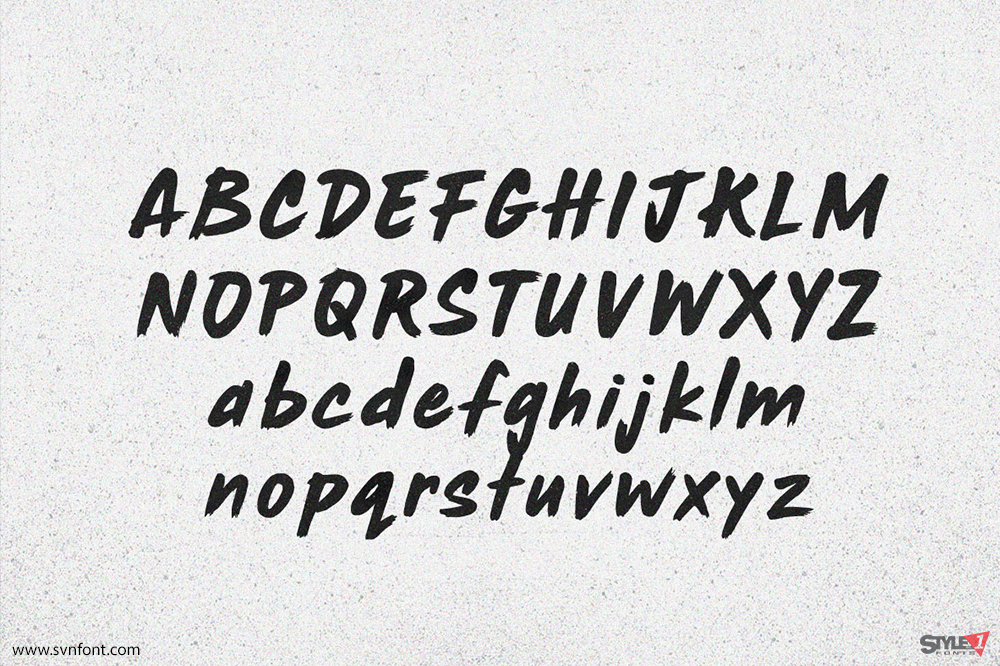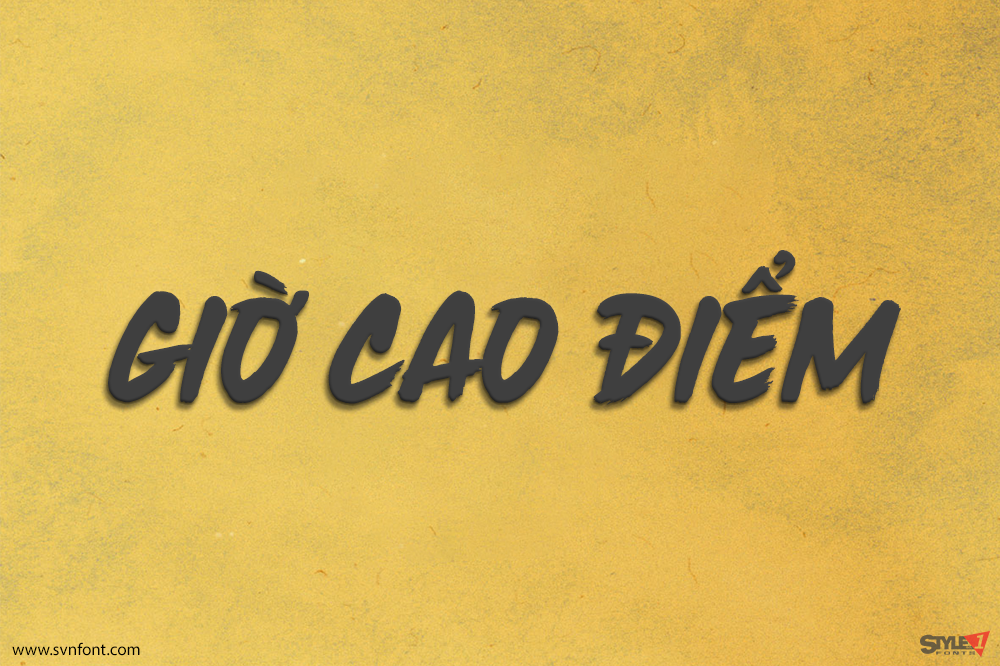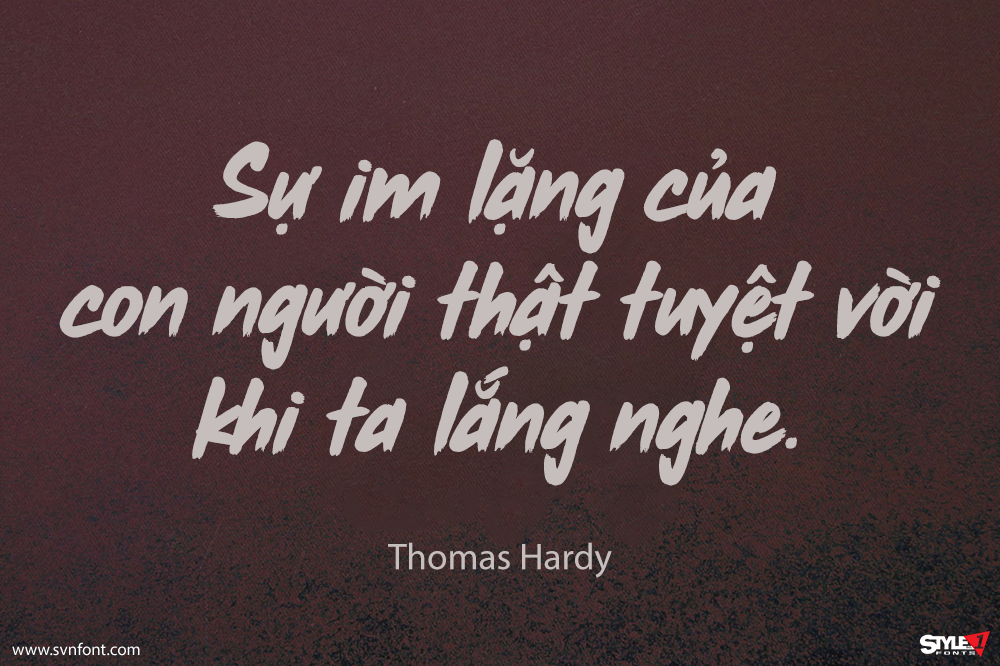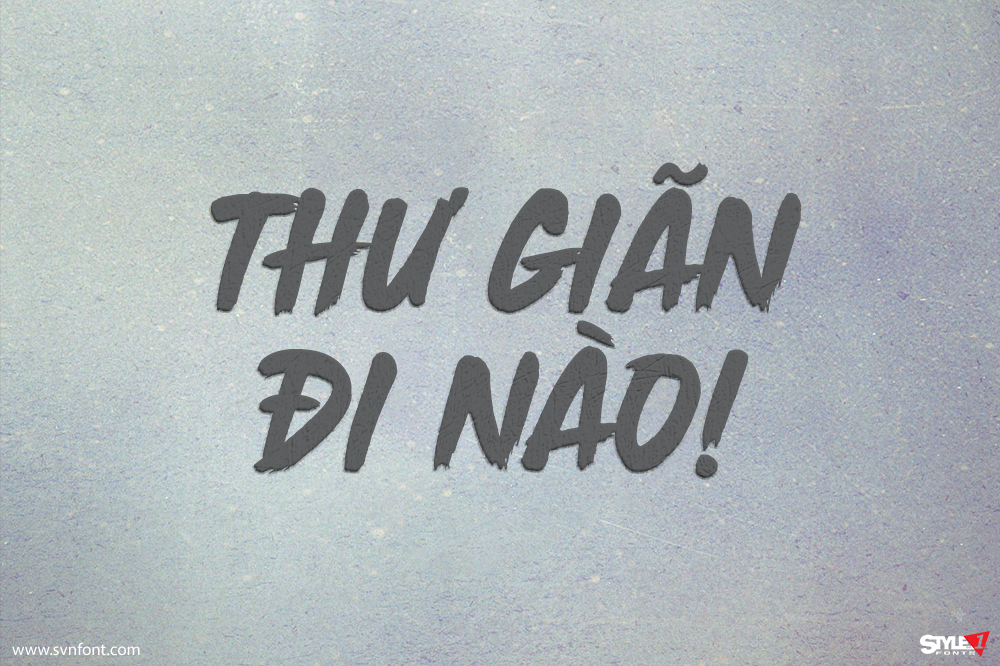
Rush Hour Font được thiết kế bởi BLKBK, với mục tiêu khơi gợi cảm hứng từ sự kết hợp giữa sắp chữ và chữ viết tay mang dấu ấn mực và bút brush. Font mang cảm giác tự nhiên, giàu năng lượng và đầy cảm xúc.
Rush Hour đặc biệt phù hợp cho thiệp cưới, tiêu đề, logo công ty, áo thun, câu trích dẫn và nhiều ứng dụng thiết kế khác — và nó còn thể hiện rất tốt trong nhiều bối cảnh sáng tạo hơn nữa.